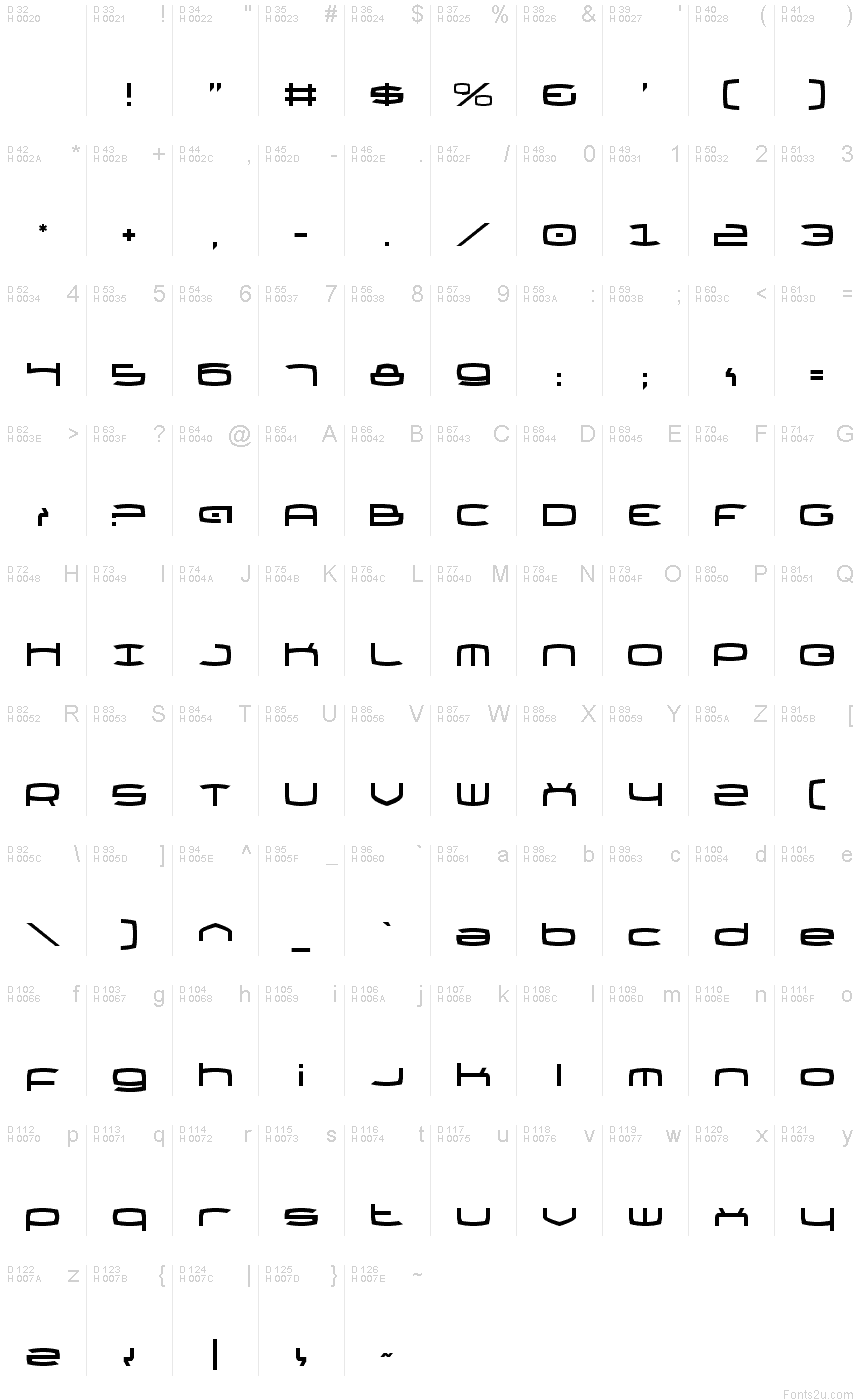
Thundergod
Thundergod od Iconian Fonts to darmowy, techniczny krój pisma typu display, wyróżniający się szerokim, futurystycznym charakterem i niemal monolinearnym spokojem. Litery przypominają rozciągnięte, płynne mosty i płytkie łuki, z płaskimi wierzchołkami, głębokimi krzywiznami oraz oszczędnym, technicznym rytmem. Nadaje to krojowi elegancką, sci-fi prezencję, która nie sprawia wrażenia kruchości.
Świetnie sprawdzi się w logo gier, plakatach science-fiction, oprawach muzycznych, tytułach streamingowych oraz wyrazistych nagłówkach, gdzie darmowy font ma wyglądać syntetycznie, ale nie zimno. Wykorzystaj go, gdy chcesz, aby krótkie hasła lub branding przypominały nowoczesne maszyny – zaokrąglone łączenia zachowują płynność, podczas gdy kształty pozostają sztywne i architektoniczne.